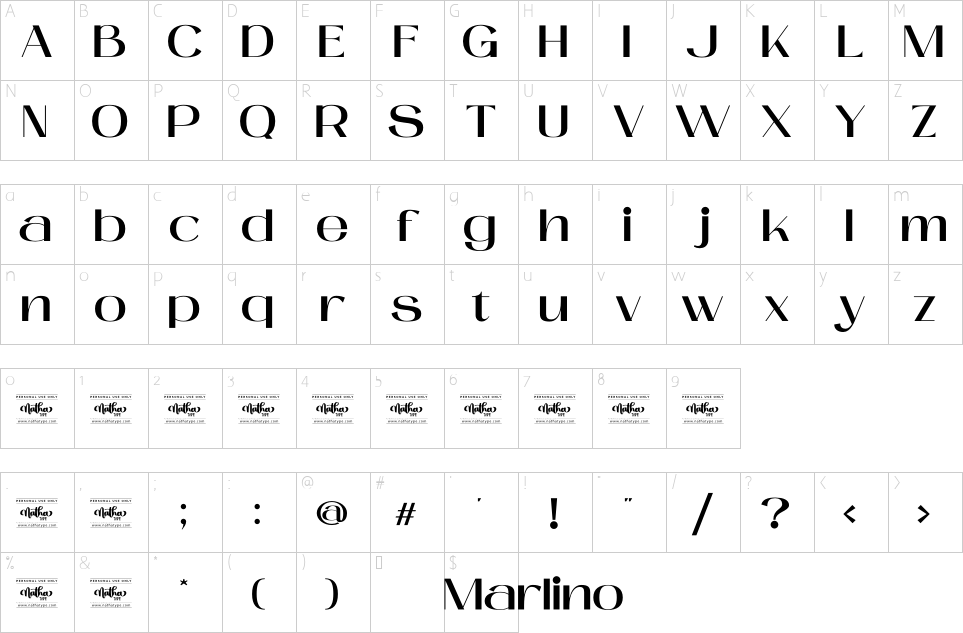
A fonte Marlino é uma escolha perfeita para quem busca uma elegância sofisticada e um toque moderno em suas criações digitais. Desenvolvida por Natha Type, esta fonte é uma ótima opção para quem busca um equilíbrio entre seriedade e modernidade. O design cuidadoso de Marlino inclui linhas finas e espessas bem equilibradas, garantindo um resultado fluido e de alta qualidade. Marlino já foi descarregada 2,156 vezes, o que prova a sua popularidade e qualidade. Essa fonte é ideal para aplicativos de texto e design gráfico, dando um toque único e sofisticado a qualquer obra. Seja para criar materiais corporativos, design de jogos, gráficos ou até mesmo para trabalhos acadêmicos, Marlino adicionará uma dimensão especial a seu projeto. Para adicionar esta fonte ao seu projeto, é só fazer o download gratuito.